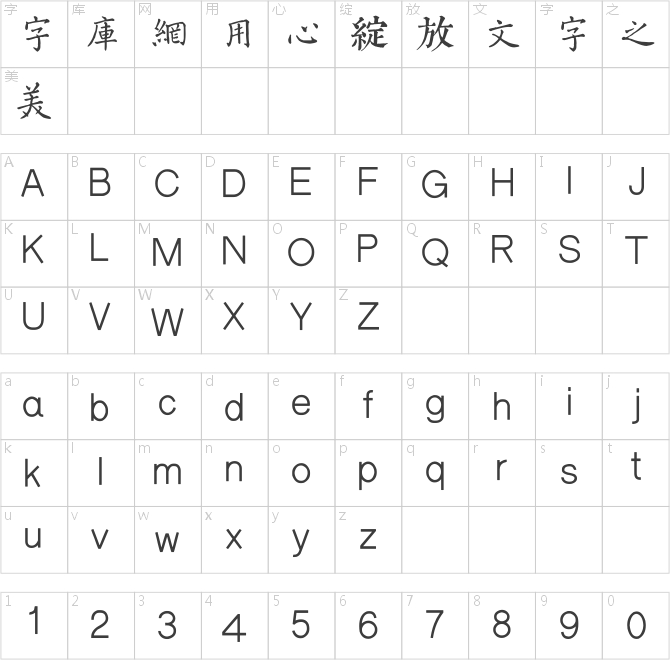
邯郸卷菱湖千字文
卷菱湖(1777~1843),江户时代後期书法家。生于越後国巷(今日本新瀉市西蒲区)。原姓池田,後改姓卷,名大任,字致远、起严,号菱湖,别号弘斋。後人称之为右内。
卷菱湖改变了明治维新时期政府内御用书法家的流行体。据传,他的学生超过万人。与市河米庵、贯名海屋并称“幕末三笔” 。卷菱湖幼年生长在新瀉町,那里寺院的抄经手对他影响很大。在他19岁时,母亲去世,这时的日本进入了江户时代。他拜画家龟田鹏斋为师,学习诗词、书法。他一生倾心于中国晋、唐时期书法??檠邢芭费粞?褚遂良。行书以李邕,王羲之为师。草书以《孝经》、《书谱》、《十七帖》、《绝交书》为临本。隸书则偏爱《曹全碑》。
卷菱湖在29岁时,著《十体流源》一书,并开设书院“萧远堂”。在他53岁时,在近衛家偶见贺知章《孝经》,为之倾倒。他一生善诗好酒,卒于天保14年,享年67岁。